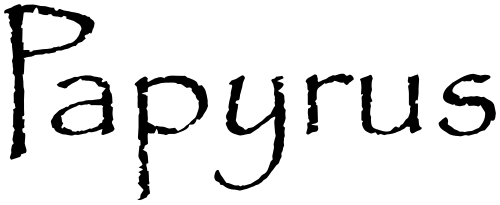
Papyrus は、グラフィック デザイナー、イラストレーター、ウェブ デザイナーの Chris Costello がデザインした書体です。1982 年に作成され、Linotype社からリリースされたこの書体は、角が粗く、曲線が不規則で、大文字の水平線が太いなど、多くの特徴を備えています。
歴史と概要
コステロは1982年、23歳で大学を卒業したばかりのときにこのフォントを作成した。聖書を勉強していた彼は、聖書の時代の中東で書かれたフォントがどのようなものだったかを思いついた。[1]彼は6か月かけてカリグラフィーペンとテクスチャードペーパーを使ってこのフォントを手描きした。コステロは、2000年前に英語のテキストがパピルスに書かれたとしたらどのようなものだったかを表すフォントが目標だったと述べた。[2]翌年、コステロはLetrasetと一緒にこのフォントをリリースした。Papyrusには、ざらざらしたエッジ、不規則な曲線、大文字の水平線の高さなど、いくつかの際立った特徴がある。この書体の現在の所有者であるITCは、これを「伝統的なローマン体の文字の優雅さと、高度な技術を持つカリグラフィーの手作りの外観を効果的に融合させた珍しいローマン体書体」と表現している。[3]コステロはフォントの権利を750ドル(2023年の価値で2,400ドルに相当)で売却し、2017年現在、2000年以降MacまたはMicrosoftのオペレーティングシステムを搭載したすべてのパソコンにフォントが含まれているにもかかわらず、依然として「非常に低い」使用料を受け取っていると述べています。[1]いずれにせよ、コステロは「(フォントが)あらゆる用途に使用されることは意図していませんでした。使いすぎです」と主張しています。[4]
可用性
Papyrusは、Windows用の多くのMicrosoftプログラムに含まれています。[5] macOSには、基本インストールの一部としてPapyrusフォントが含まれています(2003年にリリースされたバージョン10.3 Panther以降)。[6]
大衆文化における受容と利用
長年にわたり、パピルスはグラフィックデザインにおいて、通常は本来意図されていない状況で、いたるところで使用されていることで悪名を馳せてきました。この書体に対する批判は、Comic Sansに対する批判と似ています。[7] 2008年には、この書体の遍在性と誤用を記録するために、「Papyrus Watch」というウェブサイトが作成されました。[8]
ウェブコミック 「XKCD」では、登場人物がパピルスで印刷された誕生日カードを「タイポグラフィオタク」に渡して困らせている。[9]
映画『アバター』では、標準的なパピルスが字幕に使用され、修正版が映画のタイトルに使用されている。[10] [11]映画での使用は、ライアン・ゴズリングが出演した2017年のサタデー・ナイト・ライブのスケッチ「パピルス」で強調され、[1] [12]シャキーラのグッズ、水タバコバー、ノーブランドの紅茶会社でも広く使用されていると主張された。 [13]両方のアバター映画のプロデューサーであるジョン・ランドーは、スケッチが2作目の制作中にアバターの関連性を保つのに役立ったと主張している。 [14]アバターフランチャイズの拡大に備えて、アバター:ザ・ウェイ・オブ・ウォーターでは、映画シリーズがTorukと呼ばれる独自のフォントに変更された。[14]パピルスは今でも字幕に使用されている。[15] 『ザ・ウェイ・オブ・ウォーター』の公開後、ゴスリングはサタデー・ナイト・ライブの2作目の短編『パピルス2』に主演したが、その中で続編の莫大な予算にもかかわらず、書体が単に太字に変更されただけであることに気付いた。[16]
UndertaleにはPapyrusというスケルトンが登場し、そのセリフはフォントで書かれています。